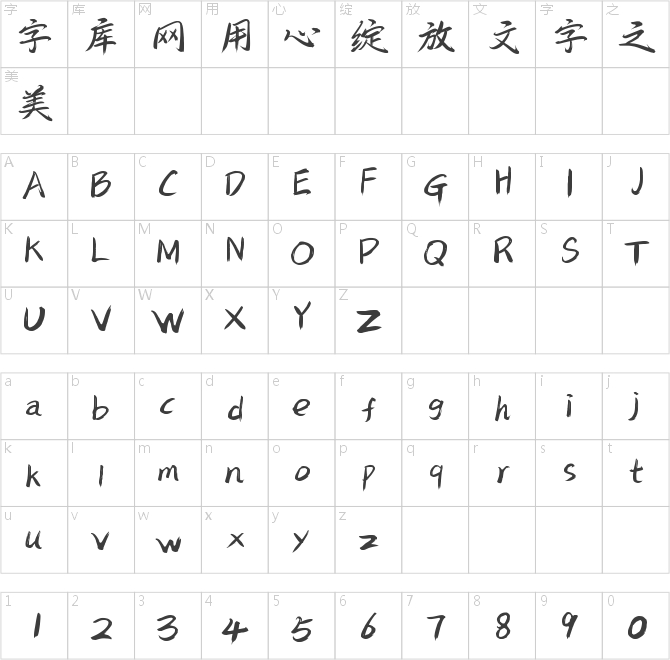
字魂245號(hào)-飛羽行書(shū) 詳情頁(yè)
字魂245號(hào)-飛羽行書(shū)
字魂245號(hào)-飛羽行書(shū)是一款手寫(xiě)字。筆畫(huà)黑中有白,行筆連綿不斷,粗處渾厚圓潤(rùn),細(xì)處勁利瀟灑,生動(dòng)活潑,適用于宣傳設(shè)計(jì)、商業(yè)廣告和產(chǎn)品包裝設(shè)計(jì)。
字魂245號(hào)-飛羽行書(shū)字體zihun245hao-feiyuxingshu字庫(kù)是一款讓人賞心悅目、百看不厭的中文字體,適合各類(lèi)廣告和產(chǎn)品包裝設(shè)計(jì)應(yīng)用,字體大小24.48MB,格式為ttf字體,上傳用戶(hù)是123123aaa,作者/版權(quán)方為字魂